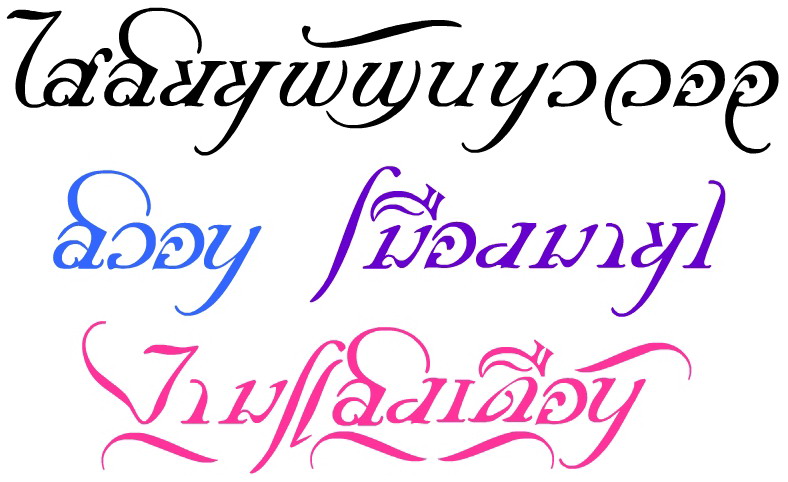
อยากรู้
อยากรู้ว่าฟอนต์ไทยจะพิมพ์ได้สองแบบในฟอนต์ชุดเดียวหรือเปล่า มีตัวอย่างที่ออกแบบไว้มาให้ดูด้วย ขอบคุณล่วงหน้าด้วยใจคาราวะ
ได้ครับ ด้วยพลังแห่ง OpenType
หลักการทำงานคือ ถ้า ก อยู่หลัง อ ให้เป็น ก แบบนี้ แต่ถ้าอยู่หลัง ข ให้เป็นแบบนี้
ยังงี้โอเคไหมครับ
ว่าแต่ ตัวอักษรคุณโคตรสนุกเลยครับ
นึกถึงโปสเตอร์หนัง ปกแผ่นเสียง เก่าๆ
แล้วมันเฮ็ดจั๋งได๋อะ ใน FL แต่มันต้องเหมือนเลือกตัวพิมพ์เล็กพิมพ์ใหญ่นะ หรือว่าต้องทำสองชุด
กรณีนี้คุณต้องทำสองชุด แล้วใส่ opentype กันขี้พุ่งเลยครับ หรือไม่ก็ใช้วิธี เปลี่ยน font เอา
ช่วยอธิบายให้ละเอียดหน่อยได้มั้ยครับ ผมเองก็อยากรู้มานานแล้วเหมือนกัน  :22:
ละเอียดคงไม่ได้ครับ
เพราะจะงงกันไปใหญ่
อธิบายแบบนี้ครับ
ในช่องglyphจะมีรูปอักษรที่ต้องการอวดลีลา
เรียงเป็นชั้นๆ แบบ Layer ครับเพราะที่อยู่ของมัน
คือช่องนั้นช่องเดียวถูกกำหนดจากองค์กรunicodeแล้ว
ถือว่าเป็นที่อยู่ที่ไปเปลี่ยนแปลงไม่ได้
แต่ต่อเติมได้ เป็นตึกหลายๆชั้นในที่ดินเดิม
การประกวด fontรอบนี้จะอบรมในประเด็นนี้ด้วย
(ตามแผนที่ว่าจะทำ เช่นกรณีตัวอาลักษณ์)
ใครได้อบรมก็เอาความรู้มาเผื่อกันในนี้ด้วยครับ
อ๊ะ อย่างนี้ท่าไม้ตาย 2 ก็ถือว่าเป็น multiple master เปล่าครับ
อาจารย์ครับ แล้วถ้าเราจะเพิ่มเลเยอร์เข้าไปในกลิฟแต่ละกลิฟนี่ต้องทำยังไงครับ ส่วนคำสั่งให้มันปรากฏกายเราสามารถคีย์เข้าไปในฟอนต์แล็บได้เลยมั้ยครับ(ที่ไหน) หรือต้องใช้โปรแกรมอื่นในการสร้างฟอนต์แบบนี้